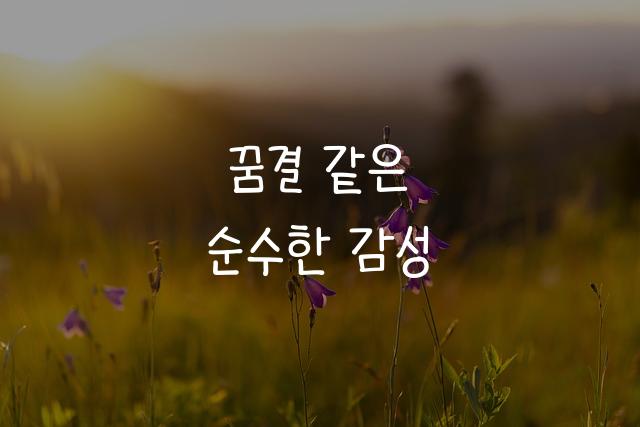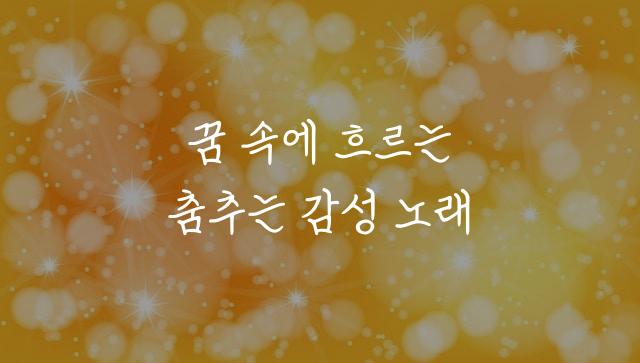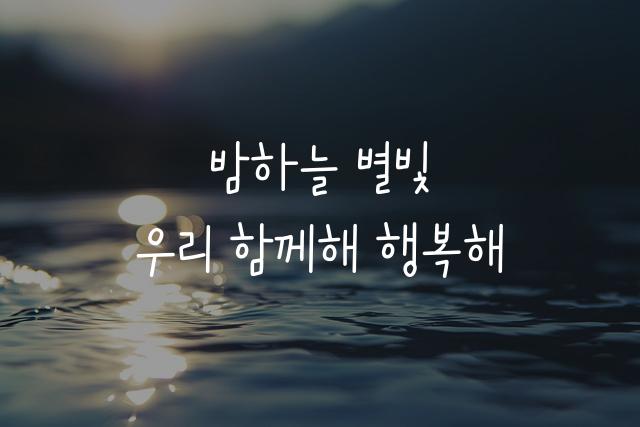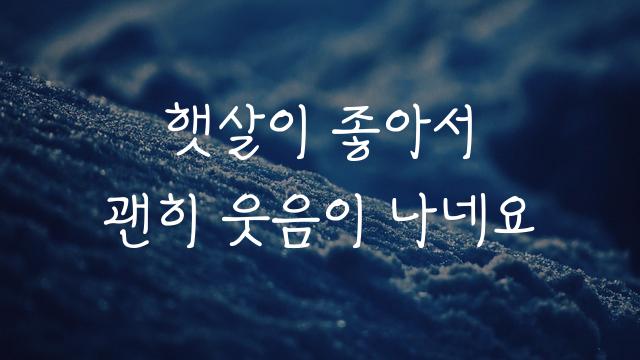
교보손글씨 2023 우선아는 동글동글하고 귀여운 감성이 묻어나는 기울어진 필기체 폰트입니다. 이 폰트는 부드러운 선과 개성 있는 기울기로 따뜻한 감정을 전달하며, 일상의 즐거움을 담아내기에 적합합니다.
교보손글씨 2023 우선아은(는)
둥근 스타일, 귀여운 스타일, 기울임, 감성적인, 자연감성, 부드러움, 복실복실 계열의 생김새를 가지고 있으며
출판 디자인, 출판물 제목, 일기/편지 등에서 자주 활용되며, 효과적인 메시지 전달에 적합합니다.
이 폰트는 출판/미디어, 크리에이티브, 문화/예술 분야에 잘 어울리며,
감성적인, 부드러운, 예술적인 느낌을 담고 있는 것이 특징입니다.